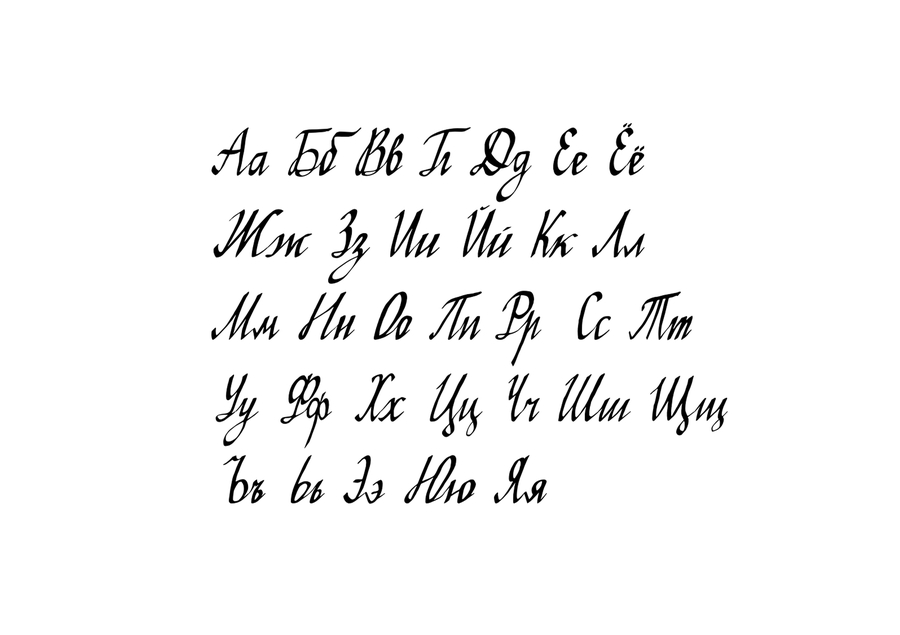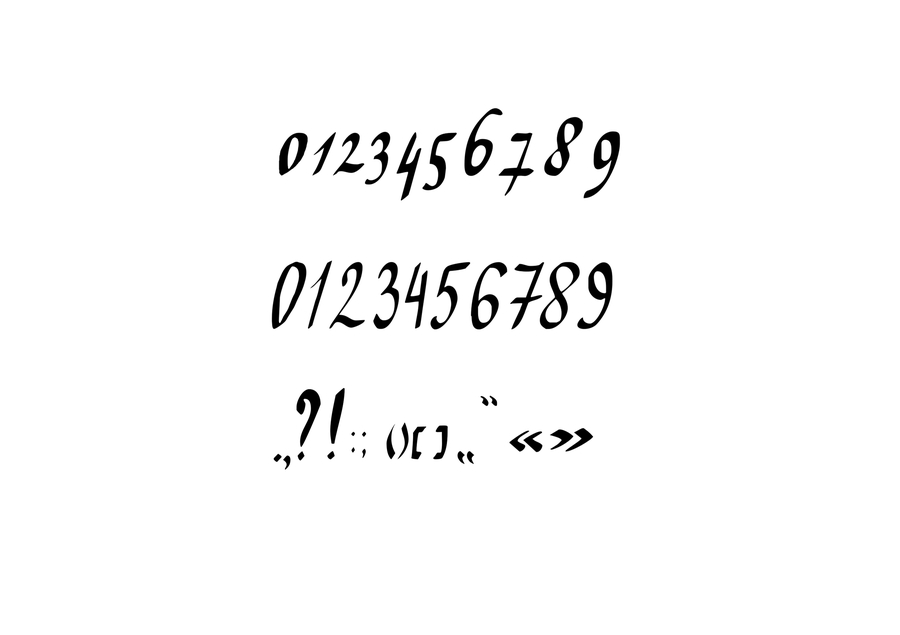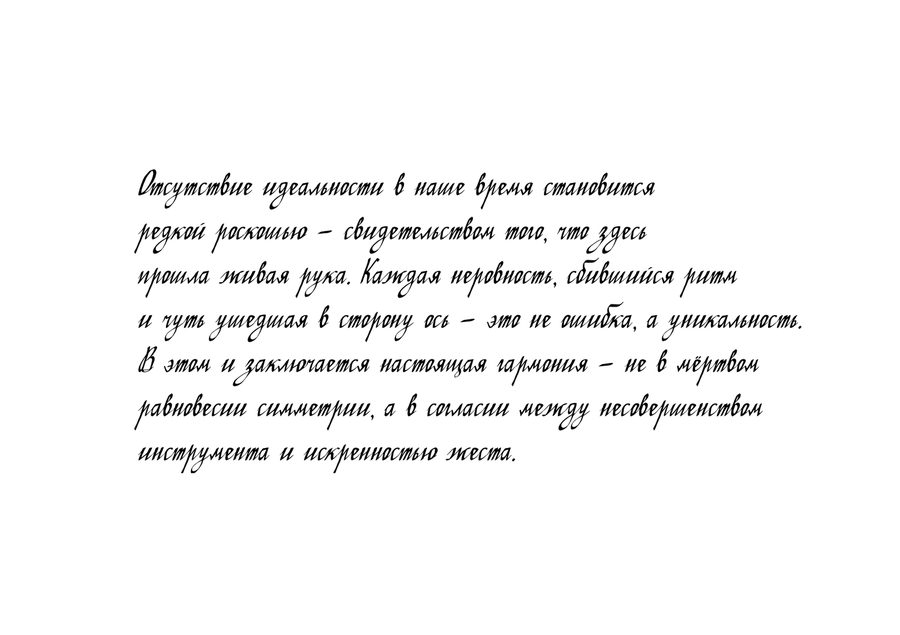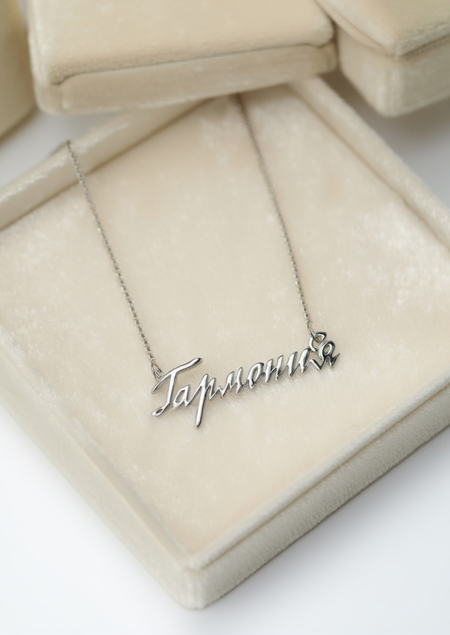
Гармония — это не только про баланс и идеальность, а про реальность.
В современности принято всё доводить до идеала, делать максимально пластмассово и без жизни. Неидеальность жизни и её красота заключены в штрихах, неровностях, которые не являются ошибкой, а началом чего-то нового
Концепция шрифта в «несильная гармоничность» — это честность. Шрифт не притворяется идеальным каллиграфическим инструментом. Он такой, какой есть. Эта неровность создает ощущение тепла, рукописного письма, которое невозможно подделать массово.